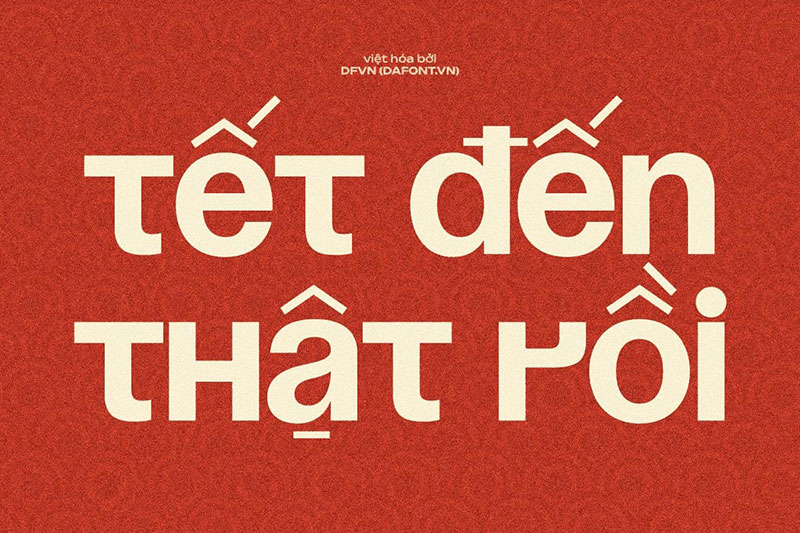
Font Soyuz Grotesk Việt hóa v2.0 – Bản nâng cấp hoàn thiện từ DFVN, nâng cấp glyph, tối ưu kerning, trải nghiệm hoàn thiện.
Soyuz Grotesk Việt hóa v2.0 là phiên bản nâng cấp toàn diện dành cho những nhà thiết kế yêu thích phong cách grotesk hiện đại, mạnh mẽ và dễ ứng dụng. Đây là bản Việt hóa được cập nhật bởi DFVN, mang đến trải nghiệm mượt mà hơn, ký tự tiếng Việt sắc nét, đồng bộ và thân thiện trong hầu hết các tình huống sử dụng.
Soyuz Grotesk là một kiểu chữ grotesk hiện đại với form chữ khỏe khoắn, đường nét dứt khoát và khả năng hiển thị rõ ràng, đặc biệt phù hợp cho tiêu đề, poster, thiết kế thương hiệu, giao diện số và các ấn phẩm truyền thông.
Phiên bản Việt hóa được tinh chỉnh mượt mà, đảm bảo đầy đủ dấu và ký tự tiếng Việt, giúp font trở thành lựa chọn nổi bật cho những dự án cần sự mạnh mẽ, tối giản và mang tính nhận diện cao.